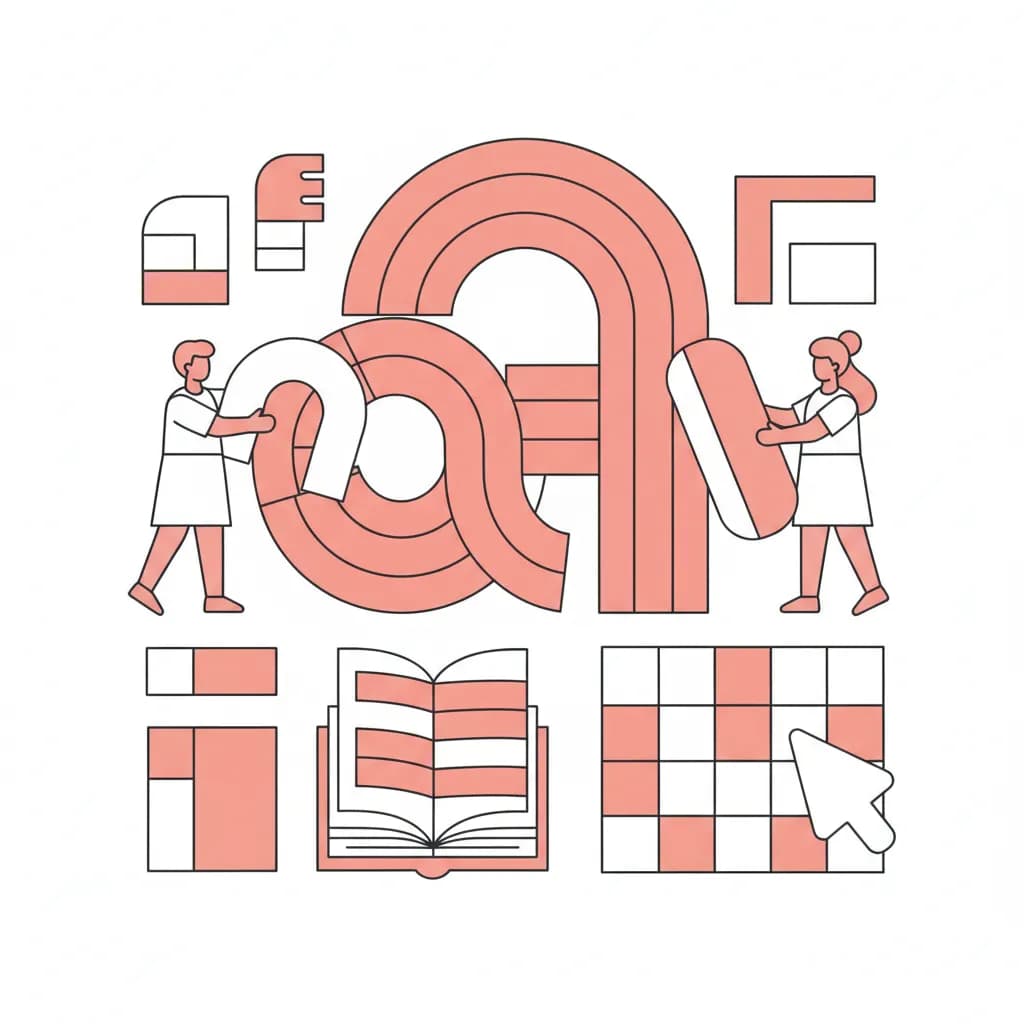
עיצוב מילים הוא הרבה יותר מסתם בחירת פונט יפה. זוהי אמנות מדויקת של העברת מסר באמצעות טיפוגרפיה, צבע, מרווחים ויחסים ויזואליים שיוצרים חוויית קריאה אפקטיבית. כשמעצבים מילים בצורה נכונה, הן לא רק נראות טוב – הן מדברות ישירות אל הקורא, מעבירות רגש, ומנחות את העין בדיוק למקום שבו אנחנו רוצים שהיא תגיע. בעולם שבו משתמשים סורקים תוכן במהירות, היכולת לעצב מילים שתופסות תשומת לב ומעבירות את המסר בבהירות היא מיומנות קריטית לכל מעצב, משווק או יוצר תוכן.
עיצוב מילים הוא תהליך מושכל של בחירה וסידור אלמנטים טיפוגרפיים כך שהמסר יועבר בצורה המדויקת והאפקטיבית ביותר. זה כולל החלטות על סוג הפונט, גודל האותיות, משקל הטקסט, מרווחים בין שורות ואותיות, צבעים, ויישור. כל החלטה משפיעה על האופן שבו הקורא תופס את התוכן – האם הוא נראה מקצועי או חובבני, רציני או משעשע, מודרני או קלאסי.
המוח האנושי מעבד מידע ויזואלי פי 60,000 מהר יותר מטקסט רגיל. כשמילים מעוצבות בצורה נכונה, הן הופכות למידע ויזואלי שהמוח קולט מיידית. לעומת זאת, עיצוב גרוע יוצר חיכוך קוגניטיבי – הקורא צריך להשקיע מאמץ נוסף כדי להבין את המסר, ובמקרים רבים הוא פשוט יוותר ויעבור הלאה. במחקרי UX נמצא שמשתמשים מקדישים בממוצע 5-7 שניות לסריקת דף לפני שהם מחליטים אם להישאר או לעזוב – ובמהלך השניות האלה, העיצוב הטיפוגרפי הוא הגורם המכריע.
בעברית, האתגר מורכב במיוחד. השפה העברית נכתבת מימין לשמאל, מה שדורש התאמות מיוחדות בעיצוב. פונטים רבים שמעולים באנגלית נכשלים בעברית בגלל הבדלים במבנה האותיות, בניקוד ובצורך בתמיכה טכנית מתאימה. לכן, עיצוב מילים בעברית דורש הבנה עמוקה של הטיפוגרפיה היהודית ושל העקרונות הייחודיים לשפה זו. כדי להבין את השורשים של הטיפוגרפיה העברית, כדאי לקרוא על טיפוגרפיה יהודית והשפעת הכתבים הקדומים על העיצוב המודרני.
עיצוב מילים מוצלח מתבסס על ארבעה עקרונות יסוד שחייבים לעבוד יחד בהרמוניה. כל עיקרון תורם להעברת המסר בצורה ברורה ומשכנעת.
קריאות מתייחסת ליכולת לזהות אותיות ומילים בקלות. פונט קריא הוא כזה שבו כל אות ניתנת להבחנה מיידית, גם בגדלים קטנים. בעברית, זה אומר שאותיות כמו ר' ו-ד', או ח' ו-ה', לא נראות זהות. לטקסט רץ (טקסט גוף ארוך), עדיף להשתמש בפונטים עם סריפים עדינים או Sans-Serif נקיים שתוכננו במיוחד לקריאה ממושכת. גודל מינימלי מומלץ לטקסט רץ הוא 16-18px במסכים דיגיטליים.
היררכיה ויזואלית מנחה את העין של הקורא דרך התוכן בסדר הנכון. היא נוצרת באמצעות שילוב של גודל, משקל, צבע ומיקום. כותרת ראשית צריכה להיות גדולה ובולטת, כותרות משנה קטנות יותר אך עדיין בולטות, וטקסט גוף בגודל רגיל. ההבדלים חייבים להיות משמעותיים – לא מספיק הבדל של 2px בין כותרת לטקסט גוף. יחס מומלץ: כותרת ראשית פי 2-3 מגודל הטקסט הרגיל, כותרות משנה פי 1.5-2.
ניגודיות מתייחסת להבדל בין הטקסט לרקע. ניגודיות חלשה (כמו טקסט אפור בהיר על רקע לבן) מקשה על הקריאה ופוגעת בנגישות. יחס ניגודיות מינימלי לפי תקן WCAG הוא 4.5:1 לטקסט רגיל ו-3:1 לטקסט גדול. כלים כמו WebAIM Contrast Checker יכולים לבדוק את היחס. ניגודיות נוצרת גם באמצעות משקל הפונט – טקסט Bold בולט יותר על רקע צבעוני מאשר Regular.
עקביות יוצרת מראה מקצועי ומסייעת לקורא להבין את המבנה. זה אומר שכל הכותרות מאותה רמה נראות זהות (אותו פונט, גודל, צבע), כל הקישורים מעוצבים באותו אופן, וכל רשימות התבליטים עוקבות אחר אותו סגנון. עקביות חוסכת זמן קריאה – לאחר שהקורא למד את המערכת פעם אחת, הוא יודע מה לצפות בכל דף נוסף. לכן, כדאי לבנות Style Guide שמגדיר את כל ההחלטות הטיפוגרפיות מראש.
עיצוב מילים אפקטיבי אינו תהליך אקראי. הנה שיטת עבודה מוכחת שתוביל אתכם לתוצאות מקצועיות בכל פעם.
שלב 1: הגדרת המטרה והקהל
לפני שבוחרים פונט או צבע, צריך לשאול: למי מיועד המסר ומה אנחנו רוצים שיקרה? קהל צעיר ודיגיטלי ידרוש פונטים מודרניים ודינמיים, בעוד קהל מבוגר יעדיף פונטים קלאסיים וקריאים יותר. מסר פורמלי (כמו מסמך משפטי) ידרוש סגנון שמור ומקצועי, בעוד מודעה שיווקית יכולה להרשות לעצמה יצירתיות רבה יותר. הקדישו 10-15 דקות לרשום את תשובותיכם לשאלות האלה לפני שממשיכים.
שלב 2: בחירת משפחת פונטים
בחרו 2-3 פונטים מקסימום לכל פרויקט: פונט אחד לכותרות ופונט אחד לטקסט גוף. אפשר להוסיף פונט שלישי להדגשות מיוחדות, אך לא יותר. הפונטים צריכים להשלים אחד את השני – לא להתחרות. שילוב נפוץ ומוצלח הוא Sans-Serif לכותרות (נקי ומודרני) ו-Serif לטקסט גוף (קריא ומסורתי), או להיפך. לעיצובים עם אופי חזק יותר, למשל הזמנות לאירועים, פונט אליאנה הוא פונט דו-לשוני סקריפט קליגרפי המתאים במיוחד לכותרות ולעיצובים חגיגיים. חשוב לבדוק שהפונטים תומכים בניקוד אם אתם עובדים עם טקסטים מקראיים או חינוכיים.
שלב 3: קביעת גדלים ומשקלים
צרו סולם טיפוגרפי (Type Scale) שמגדיר את כל הגדלים שתשתמשו בהם. התחילו מגודל הטקסט הבסיסי (בדרך כלל 16-18px) והכפילו או חלקו ביחס קבוע. יחס פופולרי הוא 1.5 (Major Third) – כל רמה גדולה פי 1.5 מהקודמת. לדוגמה: טקסט גוף 16px, כותרת H3 24px, כותרת H2 36px, כותרת H1 54px. כלים כמו Type Scale Calculator של Google Fonts יכולים לעזור לכם לחשב את היחסים האלה באופן אוטומטי.
שלב 4: התאמת מרווחים
מרווחים נכונים הם המפתח לקריאות. Line-height (מרווח בין שורות) אופטימלי לטקסט רץ הוא 1.5-1.7 מגודל הפונט – כלומר, אם הפונט הוא 16px, המרווח בין השורות יהיה 24-27px. Letter-spacing (מרווח בין אותיות) צריך להיות זהיר – בעברית, מרווח גדול מדי יכול לפגוע בזרימת הקריאה. לכותרות גדולות לעיתים כדאי להקטין מעט את ה-Letter-spacing (ערכים שליליים כמו -0.02em) כדי שהמילים ייראו צפופות ומלוכדות יותר.
שלב 5: בדיקה ועידון
לאחר שהעיצוב מוכן, בדקו אותו בהקשרים שונים: במסכים גדולים וקטנים, במצבי תאורה שונים, ועל ידי אנשים שאינם מעצבים. בקשו משתמשים אמיתיים לקרוא את הטקסט ושאלו אותם: האם זה היה קל לקרוא? האם הם הבינו מיד מה חשוב? האם הם פספסו משהו? התשובות האלה יעזרו לכם לזהות בעיות שלא שמתם לב אליהן.
גם מעצבים מנוסים נופלים לעיתים למלכודות הבאות. הכרת הטעויות האלה תחסוך לכם זמן ותשפר את התוצאות באופן משמעותי.
⚡ טעויות קריטיות שחייבים להימנע מהן:טעות נוספת היא שימוש בפונטים דקורטיביים לטקסט ארוך. פונטים מעוטרים כמו פונט רומנטיקה – שהוא פונט סריף מנוקד ומעוטר – מתאים מאוד לכותרות ולעיצובים חגיגיים, אך לא לטקסט גוף ארוך. השתמשו בפונטים מעוטרים במשורה ורק בכותרות או במילות מפתח בודדות.
טעות נוספת היא התעלמות מהקשר התרבותי. בעיצוב עברי, יש חשיבות רבה לבחירת פונטים שמתאימים לאופי היהודי או הישראלי של התוכן. לפרויקטים עם אופי מסורתי או דתי, כדאי לבחור פונטים בעלי שורשים היסטוריים. למשל, פונט הַלֵל הוא פונט סריף תנכ״י המשלב מאפיינים אשכנזים וספרדים, והוא מתאים במיוחד לעיצובים עם זיקה למסורת היהודית.
תחילה הגדירו את המטרה והקהל. פונט צריך להתאים לאופי המסר – פורמלי או משעשע, מודרני או קלאסי. בדקו שהפונט תומך בעברית ובניקוד אם נדרש, ובצעו בדיקת קריאות במכשירים שונים. אם אתם מחפשים פונט לעיצוב לוגו או מיתוג, כדאי לקרוא את המדריך המלא לפונטים לעיצוב לוגו.
Legibility מתייחסת ליכולת לזהות אותיות בודדות – האם אות ר' נבדלת מאות ד'? Readability מתייחסת לנוחות קריאת טקסט ארוך – האם נעים לעיניים לקרוא עמוד שלם? פונט יכול להיות Legible (אותיות ברורות) אך לא Readable (לא נוח לקריאה ממושכת) בגלל מרווחים לא נכונים או עיצוב מסובך מדי.
בדרך כלל 2-3 פונטים מקסימום. פונט אחד לכותרות, פונט שני לטקסט גוף, ופונט שלישי אופציונלי להדגשות מיוחדות. שימוש ביותר מדי פונטים יוצר מראה לא מקצועי וכאוטי. במקום להוסיף פונטים נוספים, השתמשו במשקלים שונים (Light, Regular, Bold) של אותו פונט כדי ליצור וריאציה.
עיצוב מילים בצורה שתעביר בדיוק את המסר הוא שילוב של אמנות ומדע. זה דורש הבנה של עקרונות טיפוגרפיה – קריאות, היררכיה, ניגודיות ועקביות – ויישום מושכל שלהם בכל פרויקט. המפתח הוא לזכור שעיצוב מילים אינו רק על יופי ויזואלי, אלא על תפקוד: האם הקורא מבין את המסר במהירות? האם הוא יודע מה חשוב ומה פחות? האם הוא מרגיש שהתוכן מיועד אליו?
תהליך עבודה מסודר – החל מהגדרת מטרות וקהל, דרך בחירת פונטים וקביעת גדלים, ועד לבדיקה ועידון – מבטיח שכל החלטה תהיה מושכלת ומבוססת על צרכי הפרויקט. הימנעות מטעויות נפוצות כמו שימוש ביותר מדי פונטים, טקסט קטן מדי או חוסר ניגודיות, תשפר באופן משמעותי את איכות העיצוב ואת חוויית המשתמש.
זכרו: עיצוב מילים מוצלח הוא כזה שהקורא לא שם לב אליו – הוא פשוט קורא, מבין ופועל. כשהטיפוגרפיה עובדת נכון, היא נעלמת לטובת המסר עצמו. וזו בדיוק המטרה.